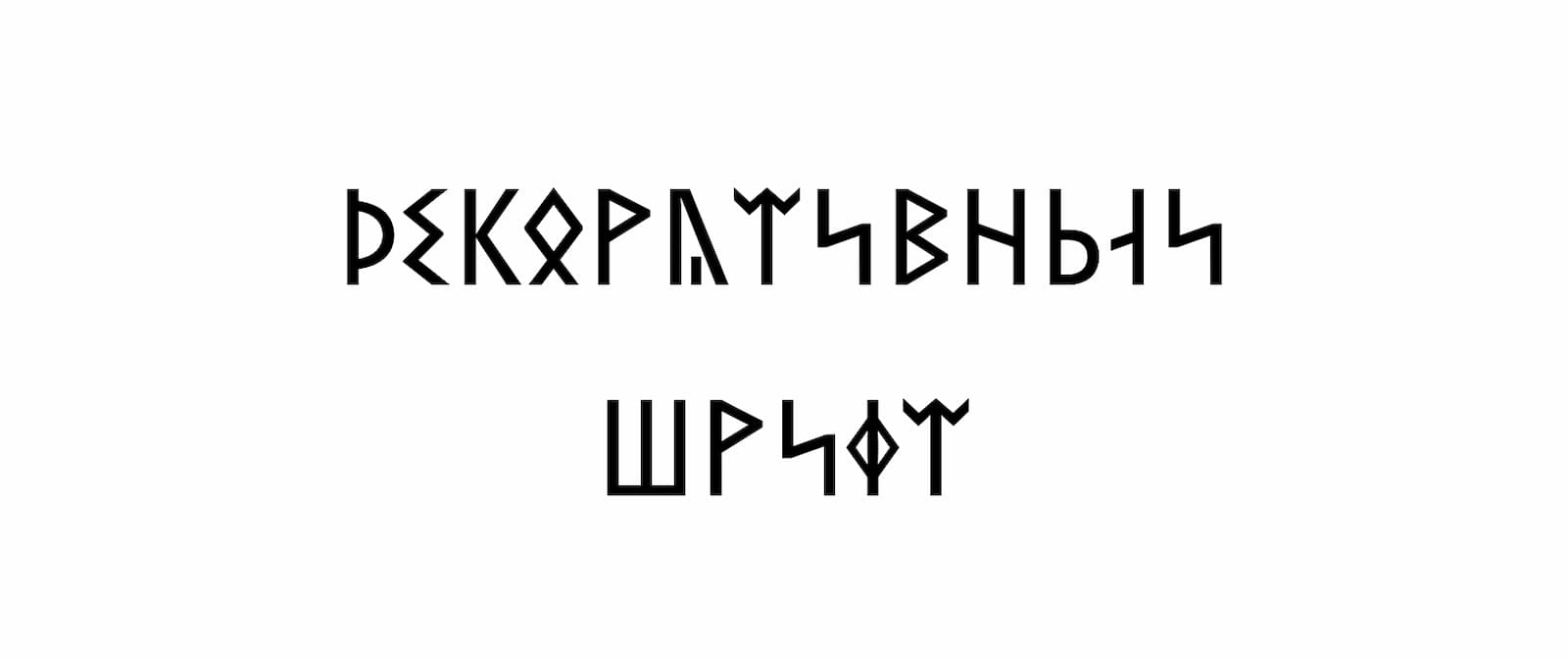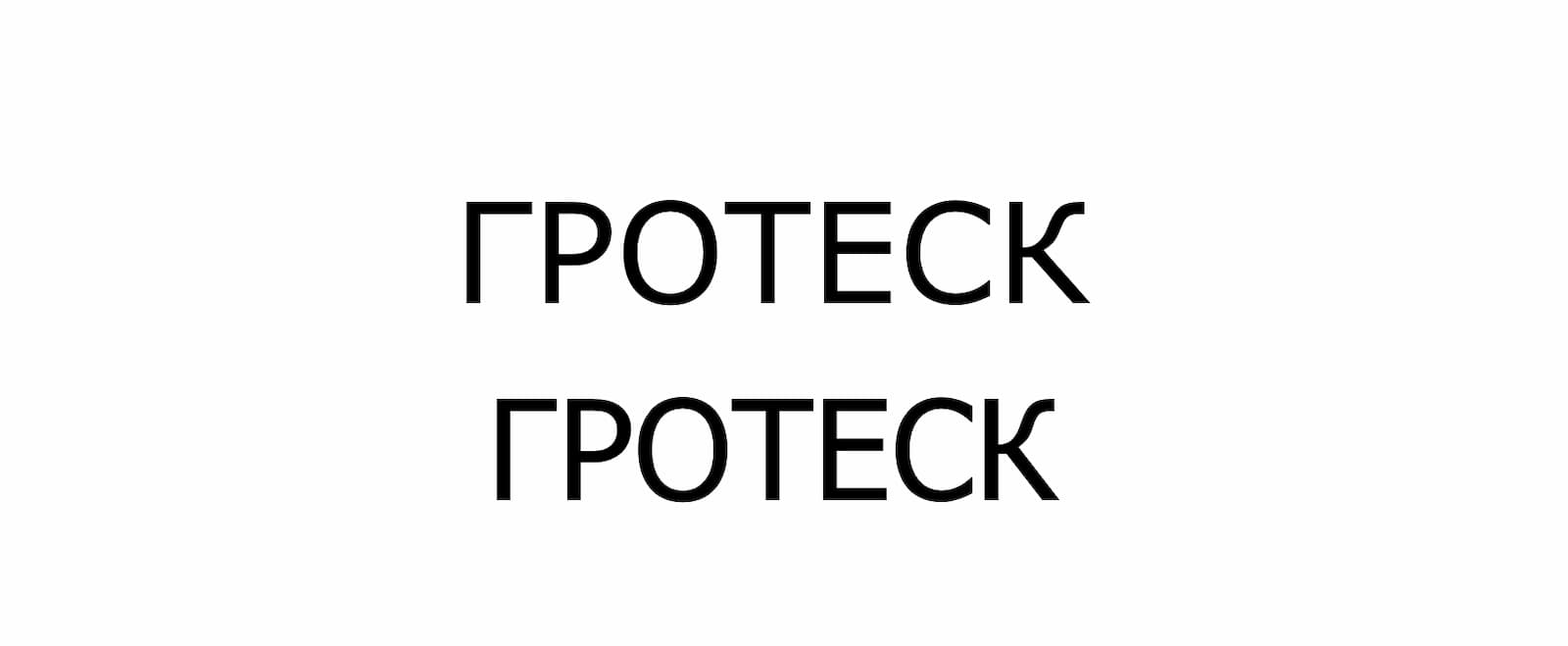
В инстаграме есть девять шрифтов для сторис и один стандартный для постов в ленте. С таким набором сложно выделиться среди конкурентов, поэтому страницы зачастую смотрятся одинаково. Создать уникальную шапку профиля, выделить ключевые моменты в публикации и красиво оформить тексты в сторис помогут разные написания. Рассказываем, как сделать красивый шрифт в инстаграме.
Почему шрифты важны в дизайне
В дизайне есть отдельное направление под названием «Типографика» — оно о том, как правильно расположить текст, выбрать нужные шрифты и грамотно определить их размеры. Шрифт — это важный элемент типографики, который помогает донести информацию правильно и быстро. Шрифты создают настроение, помогают определить главные мысли в тексте, улучшают восприятие публикаций и влияют на подсознание людей.
Психолог Кевин Ларсон проводил исследование о том, как шрифты и их компоновка влияют на эмоции. Двадцать добровольцев он разделили на две группы. Каждой группе показал разные версию журнала The New Yorker. В одной версии был грамотно выбран шрифт и правильно скомпонован текст. В другой версии были сложно читаемые шрифты и плохая компоновка текста.
Слева версия статьи с плохой компоновкой, справа с грамотной компоновкой текста
В ходе исследования психолог выяснил, что читая версию с плохой компоновкой, испытуемые плохо себя чувствовали: жмурились, морщились и долго читали текст. Участники эксперимента, которые читали другую версию статьи, меньше потратили времени на прочтение и чувствовали себя гораздо лучше. Это наглядно демонстрирует, как важен ответственный подход к выбору написания символов для текста.
Какие бывают шрифты и где их лучше использовать
В целом можно выделить три вида шрифтов: с засечками, без засечек и декоративные.
Шрифты с засечками. Иначе их называют «антиквы», а засечки — это такие чёрточки на кончиках букв. Такими начертаниями лучше оформлять длинные тексты: статьи, инструкции, резюме и др. Дизайнеры считают, что с таким шрифтом объёмные тексты лучше воспринимаются. Именно антиквы используются в традиционной книжной вёрстке.
Примеры шрифтов с засечками — наборы Georgia и Garamond
Шрифты без засечек. Их другое название без засечек — «гротески». Гротески считаются более современными и используются в коротких текстах на баннерах, в интерфейсах, в соцсетях и др. Поэтому, если вы выбираете начертание для публикаций в ленте инстаграма* или другой социальной сети, то лучше остановиться на гротеске.
Примеры шрифтов без засечек — наборы Verdana и Tahoma
Декоративные шрифты. К этой группе можно отнести рукописные наборы и шрифты, имитирующие работу печатной машинки, также сюда входят шрифты с использованием символов и эмодзи. Такие написания подходят для заголовков, логотипов или оформления коротких надписей в сторис вашего аккаунта.
Пример декоративного шрифта — Segoe UI Historic
Тот, кто работает с типографикой, должен помнить, что выбранные вами символы в текстах и заголовках должны быть читаемы — людям не хочется прилагать больших усилий, чтобы разбирать написанное. Также стоит помнить и про обилие разных начертаний и цветов. Дизайнеры советуют использовать не более двух шрифтов на одной странице.
Зачем менять шрифты в инстаграме*
Сегодня использование оригинальных шрифтов — это возможность украсить и выделить свой профиль в инстаграме*, среди множества других. Особое значение стиль текста играет в сторис. Этот формат обычно привлекает больше внимания, так как находится в самом верху ленты — к тому же у сторис высокий уровень вовлечения пользователей, благодаря интерактивным элементам.
Красивый шрифт в инстаграме* поможет блогерам, smm-специалистам и сторисмейкерам создавать креативный контент и поднимать охваты страницы.
Подборка статей для тех, кто хочет начать зарабатывать в инстаграме*:
● Профессия «Сторисмейкер» — кто это и чем занимается
● Как блогеру зарабатывать в instagram*: 5 способов
● Как стать SMM-специалистом с нуля: подробное руководство для новичков
Как сделать красивый шрифт в инстаграме* онлайн
Самый простой способ создать новый шрифт для публикаций в соцсети — использовать онлайн-сервисы. Они довольно просты в использовании: вводите текст вашей публикации, и сервис предоставляет список вариантов в разных окошках. Тот вариант, который вам больше понравится, нужно скопировать и вставить в инстаграм*.
Fine Words
В бесплатном сервисе Fine Words много разнообразных наборов. В Fine Words можно быстро изменить шрифт в любом тексте. Русские буквы поддерживаются не во всех вариантах, поэтому там, где их использование невозможно, сервис будет заменять на английские. Для удобство можно настроить фильтр, чтобы отображались только варианты с поддержкой русского языка.
Сервис Fine Words предложит разные начертания, которые поддерживаются в инстаграме*, вконтакте и других соцсетях
Хайп Тайп
У онлайн-генератора «Хайп Тайп» большая база шрифтов, более 50 различных вариантов, также есть наборы с добавлением эмоджи. На главной странице сайта можно перейти в раздел «Другие сервисы» и выбрать пресеты для обработки фото или добавить переносы строк в публикации для инстаграма*, чтобы в текстах были абзацы.
Так выглядит подбор шрифта в сервисе «Хайп Тайп»
Pretty Font
В генераторе Pretty Front можно не только выбрать понравившееся начертание, но и добавить различные украшения в текст: виньетки, символы, эмоджи и графические элементы. Единственный минус — все русские буквы сервис переводит на латиницу.
Добавление украшений и выбор шрифта в сервисе Pretty Font
Canva
Популярный сервис Canva подходит не только для создания шрифтов, но и для создания макетов, баннеров и других элементов графического дизайна. В текстах можно менять оформление текста, подбирать цветовую гамму, изменять угол наклона и выбирать нужный размер.
В сервисе Canva можно менять шрифт на готовых шаблонах или создавать свои публикации. В платной версии в сервис можно добавить свои наборы символов
Как сделать красивый шрифт в инстаграме* c помощью телеграм-ботов
Чтобы начать работу с ботом, вам нужно скачать мессенджер телеграм и зарегистрироваться в нём. Затем в строке поиска вводите название бота и нажимаете на кнопку «начать». После этого вы сможете ввести свой текст и выбрать понравившийся шрифт. Мы выбрали два бота, которые могут быстро поменять шрифты в ваших текстах.
TexterAsBot
Телеграм-бот @TexterAsBot попросит вас подписаться на сторонний телеграм-канал и после этого вы сможете отправить боту сообщение с текстом вашей публикации. В ответ на ваш запрос бот пришлёт различные варианты. Скопируйте тот вариант, который вам понравится и вставьте его в инстаграм*.
12 разных шрифтов от телеграм-бота TexterAsBot
Телеграмм-бот TextMagicBot
Этот бот работает по тому же принципу, он поможет создать около двадцати шрифтов на основе отправленного текста. Однако @TextMagicBot работает только с латинскими буквами.
Телеграм-бот TextMagicBot предлагает более 15 разнообразных вариантов
Как изменить шрифт в инстаграме* с помощью UNICODE
Поменять шрифт в профиле, постах и сторис поможет способ кодирования Unicode. По сути, это большая таблица символов всех языков мира, которая доступна на персональных компьютерах Windows и MacOS.
Таблица символов Unicode для Windows
В таблице вы найдёте стрелки, точки, подчёркивания, разные буквы и знаки. Вот как найти таблицу символов на разных операционных системах:
- windows — чтобы открыть таблицу символов на компьютерах с Windows, нужно в строке поиска рядом с кнопкой «Пуск» ввести «Таблица символов»;
- macOS — на компьютерах с MacOS нужно открыть любой текстовый редактор и в правом верхнем углу нажать на кнопку «Правка», а затем выбрать «Специальные символы».
Unicode не всегда удобен в использовании, так как каждый символ необходимо находить отдельно и по очереди вводить вручную с компьютера. Этот способ подойдёт для оформления шапки профиля, а для сторис и постов, лучше выбрать более простые варианты: онлайн-сервисы или приложения.
Приложения с красивыми шрифтами для инстаграма*
В App Store и Google Play можно найти немало приложений, которые помогут создать различные шрифты для публикаций в инстаграме*. Расскажем о самых популярных.
Leto
В удобном фоторедакторе Leto есть более 500 шрифтов и стикеров для инстаграма*. Их можно перекрашивать в любые цвета и сразу добавлять в фото или видео. Также приложение поможет создать шрифты для автоматических субтитров.
Где скачать: App Store
Стоимость: 2 850 руб. в год
Создание контента для сторис в приложении Leto. Источник: Leto
Text
Графический редактор Text помогает придумывать креативные публикации для сторис. Приложение позволяет создавать интересные наборы символов, добавлять их на фотографии, также можно создавать коллажи, использовать фоны и выбирать стикеры.
Где скачать: App Store и Google Play
Стоимость: 349 руб. в год
Изменение тени и наклонов шрифтов в приложении Text. Источник: Text
InStories
У приложение для создания креативного контента Instories много функций: готовые шаблоны сторис, создание и анимация шрифтов, большой набор фото и видео, а также целая библиотека музыки, которая не блокируется соцсетями. Созданные работы можно экспортировать в высоком разрешении и загружать в инстаграм*.
Где скачать: App Store и Google Play
Стоимость: от 349 руб. в год
Анимация шрифтов в приложении InStories. Источник: Instories
Font Candy
В приложении Font Candy более 45 отобранных вручную художественных шрифтов. Можно менять изгибы текста, настраивать прозрачность и менять интенсивность тени. Также в приложение встроены картинки и различные кавычки.
Где скачать: App Store
Стоимость: от 169 руб. в неделю
Подбор шрифтов в приложении Font Candy. Источник: Font Candy
TypiMage. Typography Editor
У приложения TypiMage большая коллекция шрифтов: есть рукописные и готические, надписи на кириллице и латинице. Можно создавать не только шрифты, но и редактировать фото. Удобное приложение для тех, кто часто работает со сторис.
Где скачать: App Store и Google Play
Стоимость: от 329 руб. в месяц
Создание нестандартного шрифта в приложении TypiMage. Источник: TypiMage
Коротко о главном
Выделить свой профиль среди тысячи других страниц можно полезными текстами, качественными фото и креативными сторис. Однако есть ещё один способ, который поможет привлечь внимание подписчиков — использование нестандартных и красивых шрифтов. В статье мы собрали наиболее популярные сервисы и приложения, которые помогают создать необычные шрифты для инстаграма*.
Если вы хотите сделать интересное оформление шапки профиля, воспользуйтесь таблицей специальных символов Unicode, которая доступна пользователям персональных компьютеров на Windows или MacOS. Если нужно добавить нестандартных шрифтов в пост для ленты, то выберите один из онлайн-сервисов или используйте телеграм-боты. Если же хотите создавать креативные сторис, то присмотритесь к мобильным приложениям и редакторам фото и видео контента для инстаграма*.
Помните, что в погоне за креативностью главное — не переборщить. Шрифт может как привлечь внимание, так и оттолкнуть ваших подписчиков.